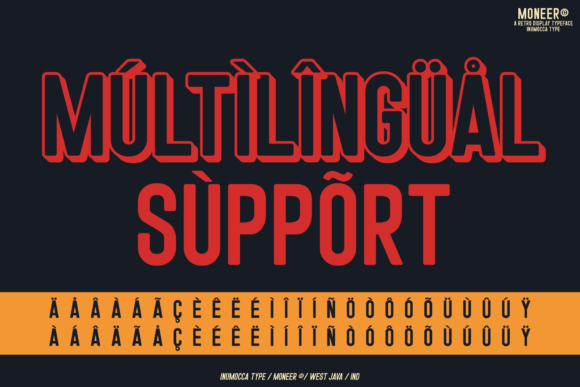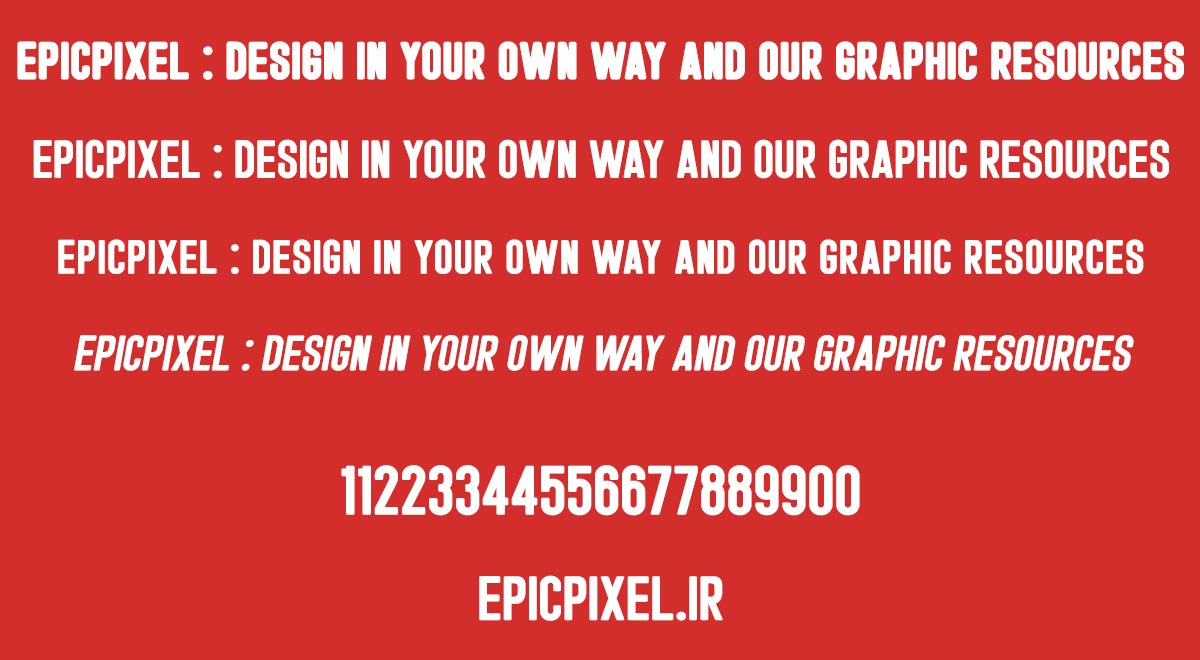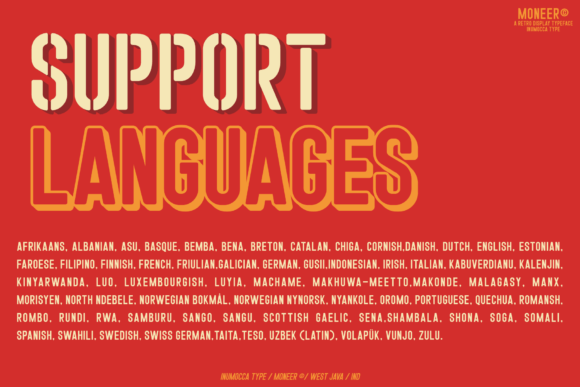
4 فونت Moneer انگلیسی
دانلود مجموعه کامل فونت Moneer انگلیسی Font منیر |
| ⭐ مجموعه فونت | دانلود فونت انگلیسی مونیر بولد Font Moneer Bold فونت منیر شادو Moneer Shadow منیر اسلانت Moneer Slant فونت منیر Moneer |
| ⭐ توضیحات | Moneer یک تایپ Retro Display است. سبک دهه 70، فونت کاراکتر ساده، پخش کامل، قدرتمند و منحصر به فرد. تایپ فیس با مجموعه سبک و برخی از فونت های خانوادگی ارائه می شود. تایپ فیس عالی برای استفاده برای پوشش پروژه شما، مانند نام تجاری، عنوان فیلم، عنوان نامه، جلد کتاب یا محتوای کتاب، جلد مجله، پوستر، نقل قول ها، لوگوها و موارد دیگر طراحی پروژه شما. – گلیف های منحصر به فرد – تنظیم کننده مونیر (OTF، TTF، WOFF) |